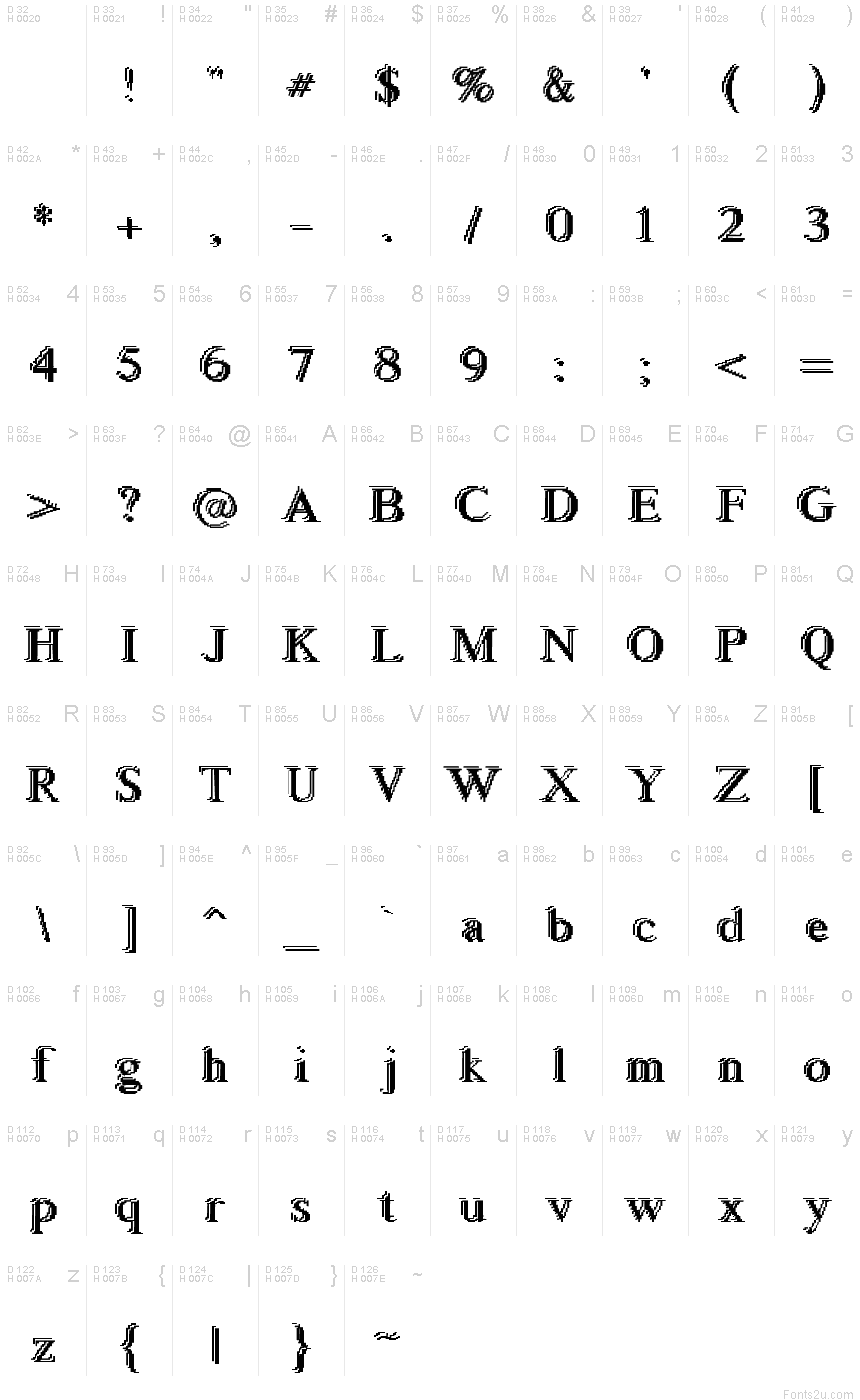
معاينة خط Blockstepped
خط Blockstepped من GemFonts هو خط بكسل مجاني يحول كل حرف إلى درجات صغيرة من المكعبات. تضفي حوافه المشرشرة والمنحوتة على أشكال الخطوط ذات الزوائد الكلاسيكية لمسة 8-بت جريئة، مثل طباعة الكتب التي كانت تُعرض على شاشات CRT القديمة. الإيقاع متقارب ولكن مقروء بشكل مدهش، مما يجعله متماسكاً كنص مع الاحتفاظ بمظهره الرقمي الواضح ذي الدقة المنخفضة.
باستخدام Blockstepped، يمكنك إضافة لمسة حادة وحنين إلى الماضي لقوائم الألعاب القديمة (ريترو)، وملصقات فن البكسل، ومجلات الهاكرز، وتصاميم البث المباشر، والشعارات، وتصاميم الملصقات. يتألق هذا الخط المجاني عند استخدامه بحجم أكبر، مما يسمح بحواف الخط المتدرجة بالوضوح؛ قم بمطابقته مع خط sans serif أحادي المسافة ونظيف للنص الأساسي للحفاظ على توازن وتنسيق التصميم بشكل مقروء.